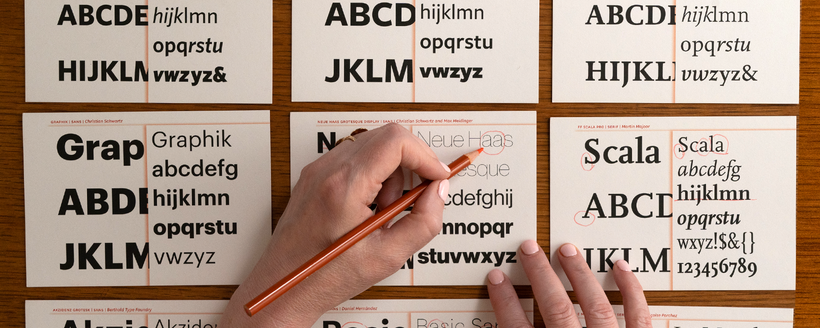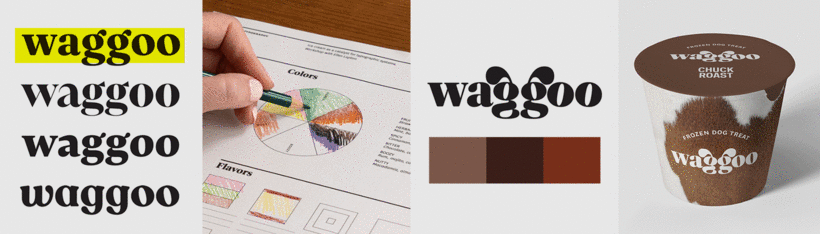
Typographie et storytelling de marque
• Valeurs et contexte
• Appellation
• Croquis de type de base
Créer un mot-symbole
• Choisir une police de caractères de marque principale
• Études de logotypes
• Tailles optiques
• Choisir une famille de type secondaire
Construire la marque
• Couleur
• Imagerie
• Applications
• Présenter votre travail
Oui, ce cours s'adresse aux designers de niveau intermédiaire qui souhaitent approfondir leur compréhension de la typographie, de la mise en page, de l'identité de marque et des techniques de narration visuelle.
Vous apprendrez à intégrer typographie et images pour créer des identités de marque engageantes, exprimer des émotions, prototyper des mises en page et concevoir des récits cohérents pour des produits et des marques.
Vous apprendrez comment le choix des polices, les systèmes de couleurs et la conception de la mise en page peuvent transmettre la personnalité, les valeurs et l'impact émotionnel d'une marque, avec des exemples concrets et des exercices guidés.
Le cours introduit l'utilisation de l'impression 3D pour le design produit, incluant la céramique texturée, la joaillerie et les emballages, mêlant artisanat traditionnel et fabrication numérique.